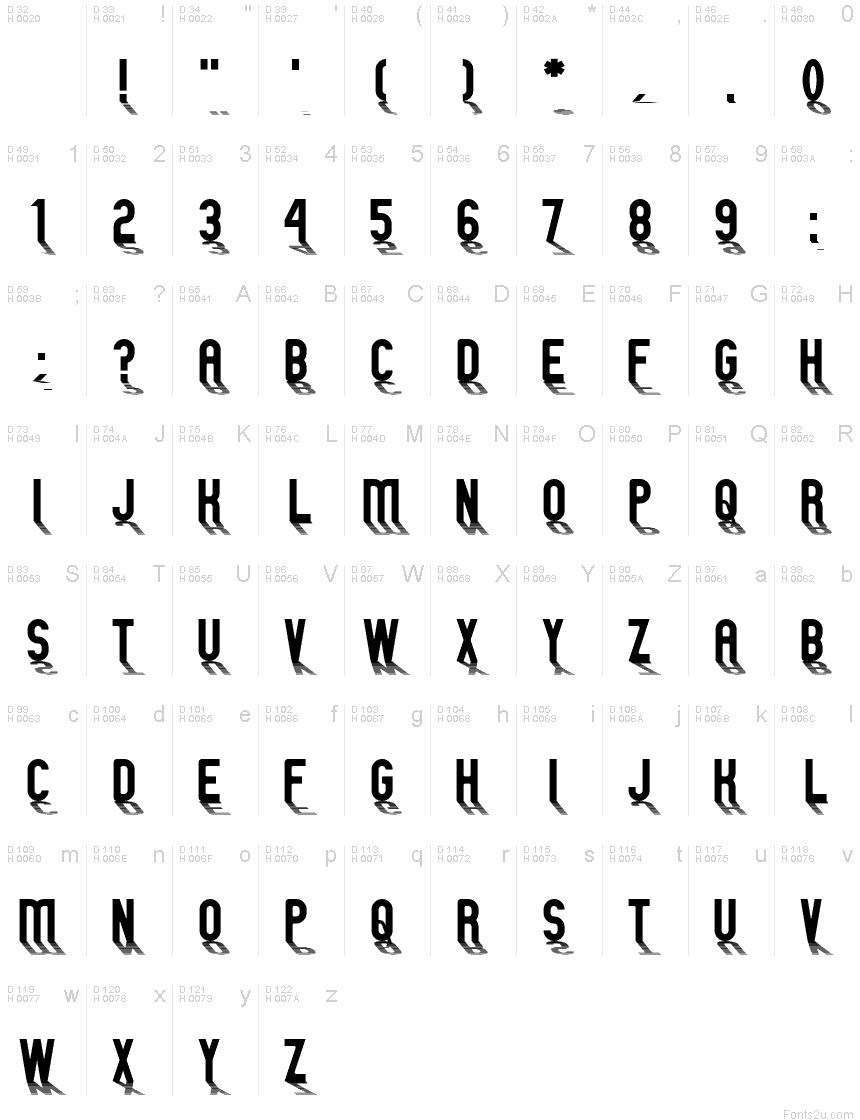
GM Exp Shadow od G.M. to darmowy, eksperymentalny krój pisma typu display, który zmienia każde słowo w odważną iluzję. Ciężkie, czarne litery stoją prosto i solidnie, podczas gdy pod nimi rozciąga się pocięty, poziomy cień, przypominający wiązkę skanera lub zniekształcone odbicie. Efekt jest szybki, dynamiczny i lekko glitchowy – idealny, gdy chcesz, aby typografia sprawiała wrażenie, jakby wibrowała na ekranie.
Dzięki GM Exp Shadow Twój tekst natychmiast zyskuje kinetyczną, pełną energii aurę, która świetnie sprawdza się na plakatach muzycznych, klubowych ulotkach, tytułach sci-fi, grafikach gamingowych, miniaturach na YouTube oraz w odważnym brandingu eventowym. Ten darmowy font najlepiej prezentuje się w dużych rozmiarach, gdzie prążkowany cień może w pełni wybrzmieć; do tekstu głównego dobierz czysty, bezszeryfowy krój, aby zachować wyrazistość i czytelność układu.
GM Exp Shadow